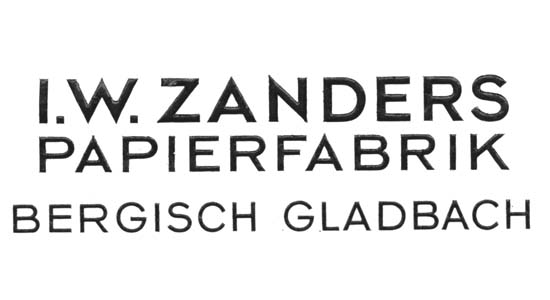
Zanders-Schrift von 1958
Ich bin auf einer Schrift aus den 60'er Jahren.
Damals wurde sie von der Firma Zanders verwendet.
Ich habe durch Zufall einen Briefbogen zu sehen
bekommen und bin nun fleißig auf der Suche!
Vielleicht kennt die Schrift ja jemand von euch?!?
welche schrift das genau ist, kann ich dir leider nicht sagen.
aber einen leicht ähnlichen charakter könnte die 'typeface' von 'neville brody' haben.
obwohl einige zeichen komplett anders aussehen.
'N' und 'A' erinnern an 'nivea' - also eher geometric:
Aber ich habe ein schönes Beispiel für das Corporate Design der Firma J.W. Zanders aus dem Jahre 1929.
Hier scheint die "Hausschrift" mit der Hand gezeichnet. Ähnlichkeiten mit real existierenden, modernen Schrifttypen wären rein zufällig.
Zweifarbiger Hochdruck auf Venil, Format 165 x 226 mm, Knick unten links. :wink: